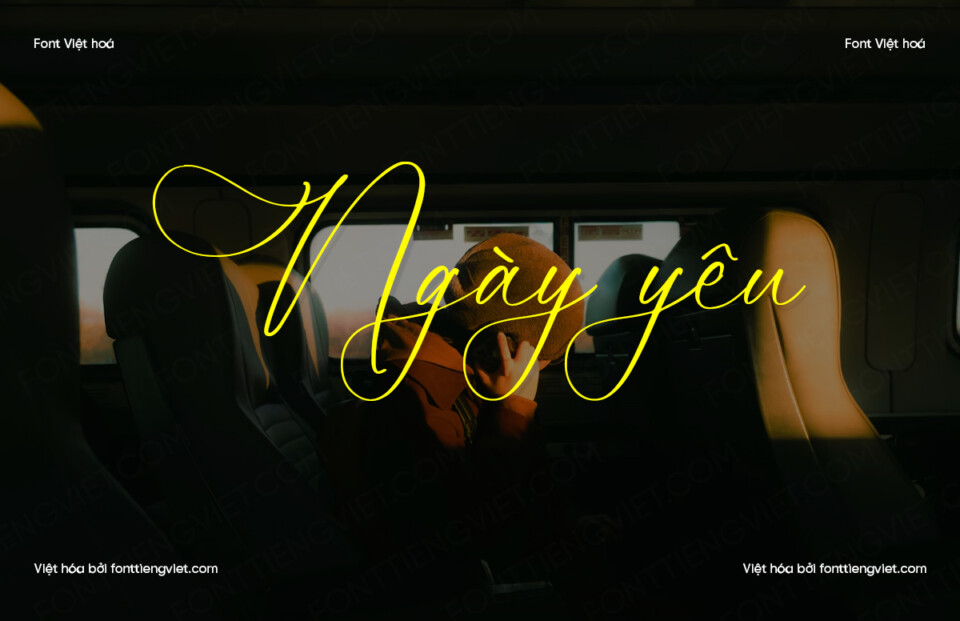
Font Việt hóa 1FTV VIP Ralsihten
Tải Ngay Font Việt hóa 1FTV VIP Ralsihten – Đẳng Cấp Thư Pháp Hiện Đại Cho Thiết Kế
Giới thiệu về bộ Font Việt hóa 1FTV VIP Ralsihten cao cấp
Trong thế giới đồ họa hiện nay, việc tìm kiếm một bộ Font Miễn Phí chất lượng để nâng tầm tác phẩm là điều vô cùng quan trọng đối với các nhà thiết kế chuyên nghiệp cũng như các bạn học sinh sinh viên. Font Việt hóa 1FTV VIP Ralsihten xuất hiện như một làn gió mới, mang lại sự kết hợp hoàn hảo giữa nét vẽ tay phóng khoáng và cấu trúc chữ hiện đại. Đây là bộ font thuộc phân khúc VIP được đội ngũ 1FTV chau chuốt kỹ lưỡng từng đường nét, giúp các ký tự tiếng Việt không bị lỗi dấu và giữ được linh hồn của bản gốc. Với phong cách Script uyển chuyển, bộ chữ này rất phù hợp cho các dự án đòi hỏi tính thẩm mỹ cao, sự sang trọng nhưng vẫn giữ được nét gần gũi, tự nhiên.
Đặc điểm nổi bật của Font Việt hóa 1FTV VIP Ralsihten
Điểm mạnh nhất của bộ Font Việt hóa 1FTV VIP Ralsihten chính là hệ thống ký tự thay thế đa dạng. Khi sử dụng, bạn có thể dễ dàng biến tấu các chữ cái đầu và cuối để tạo ra những đường cong uốn lượn đẹp mắt. Các dấu câu tiếng Việt được đặt vị trí chuẩn xác, cân đối với thân chữ, giúp tổng thể văn bản trở nên hài hòa và dễ nhìn. Đặc biệt, độ dày của nét chữ được tính toán tỉ mỉ, đảm bảo hiển thị sắc nét trên cả màn hình kỹ thuật số lẫn khi in ấn trên các chất liệu giấy khác nhau. Điều này giúp bộ font trở thành lựa chọn ưu tiên cho các bài thuyết trình tại nhà trường hoặc các dự án truyền thông giáo dục đầy sáng tạo.
Ứng dụng thực tế của Font Việt hóa 1FTV VIP Ralsihten trong sáng tạo
Sự linh hoạt là yếu tố giúp Font Việt hóa 1FTV VIP Ralsihten chiếm trọn cảm tình của cộng đồng người dùng. Bạn có thể sử dụng font chữ này để thiết kế thiệp mời, bìa sách, hay các banner quảng cáo mang phong cách nghệ thuật. Trong môi trường học đường, các thầy cô giáo có thể dùng bộ font này để trang trí bảng tin, làm tiêu đề cho các slide bài giảng thêm phần sinh động và cuốn hút học sinh. Đối với các doanh nghiệp, đây là công cụ đắc lực để tạo dựng bộ nhận diện thương hiệu, logo hay các bao bì sản phẩm cao cấp, giúp thông điệp truyền tải tới khách hàng một cách tinh tế và chuyên nghiệp hơn bao giờ hết.
Lưu ý khi sử dụng bộ font trong thiết kế chuyên nghiệp
Dù Font Việt hóa 1FTV VIP Ralsihten rất đẹp nhưng người dùng cần lưu ý về khoảng cách dòng và kích thước chữ. Vì đây là font chữ dạng viết tay với nhiều nét móc dài, bạn nên để khoảng trống rộng rãi giữa các dòng để tránh các nét chữ đè lên nhau gây rối mắt. Kết hợp bộ font này với một font chữ không chân (Sans-serif) đơn giản cho phần nội dung chi tiết sẽ là một công thức hoàn hảo để tạo nên sự tương phản thú vị, giúp người xem tập trung vào những điểm nhấn quan trọng nhất trong bản thiết kế của bạn.